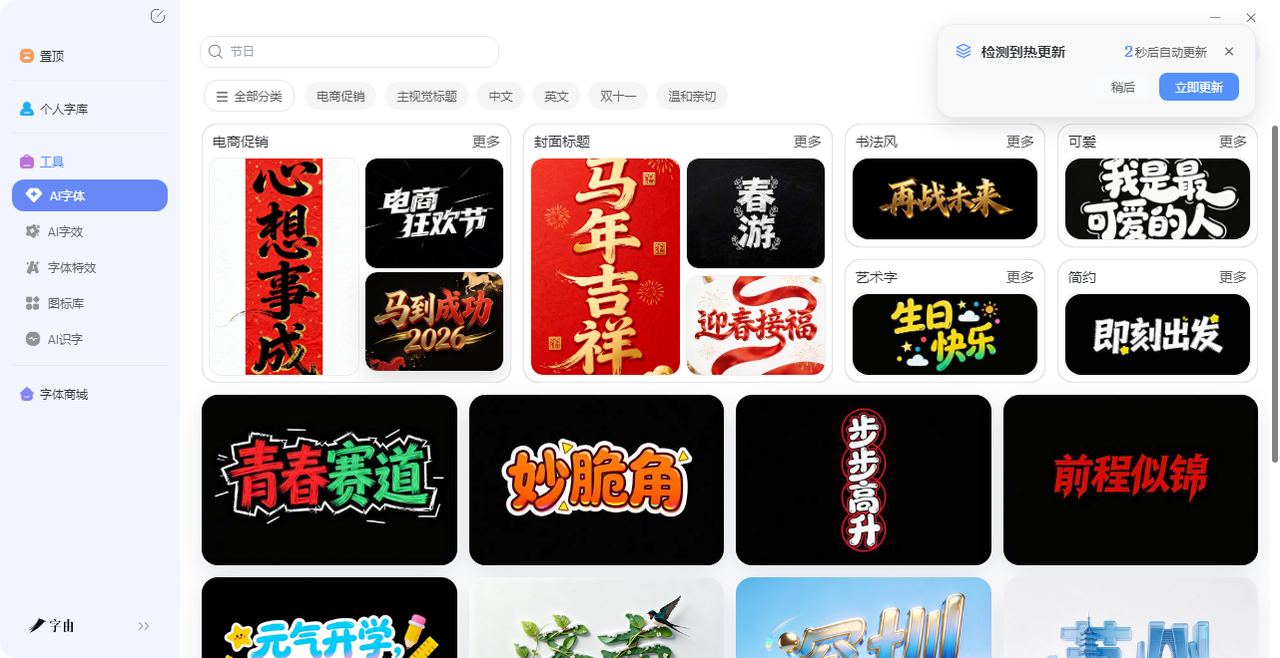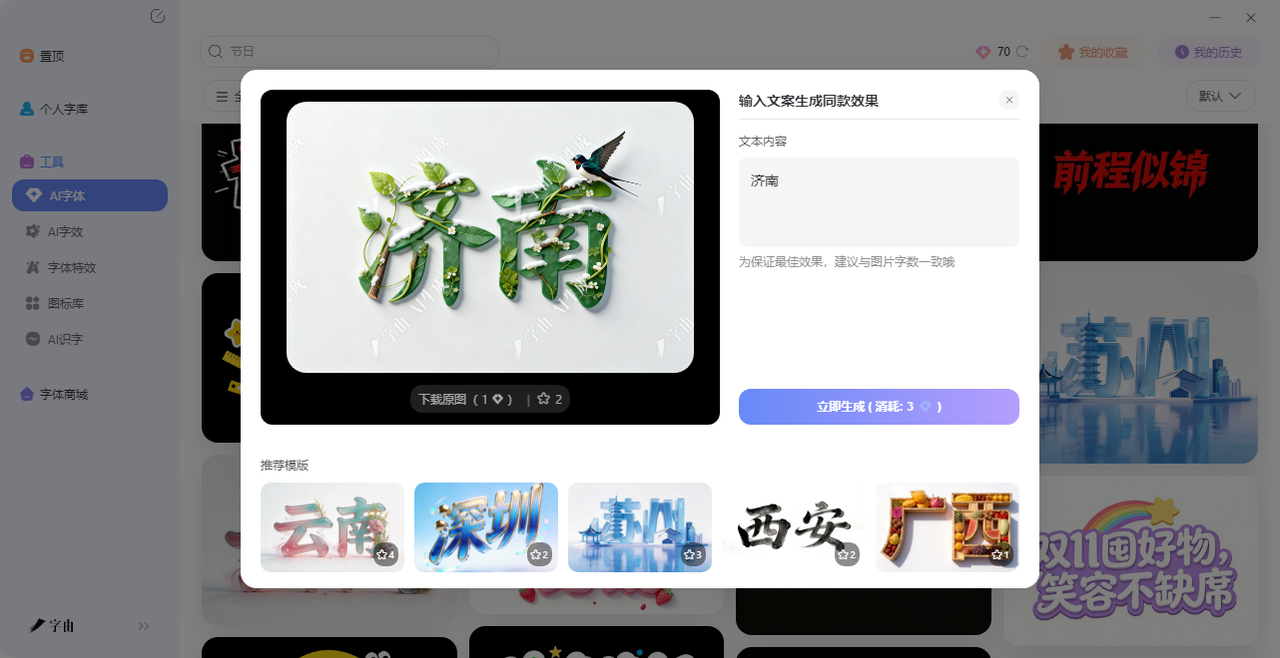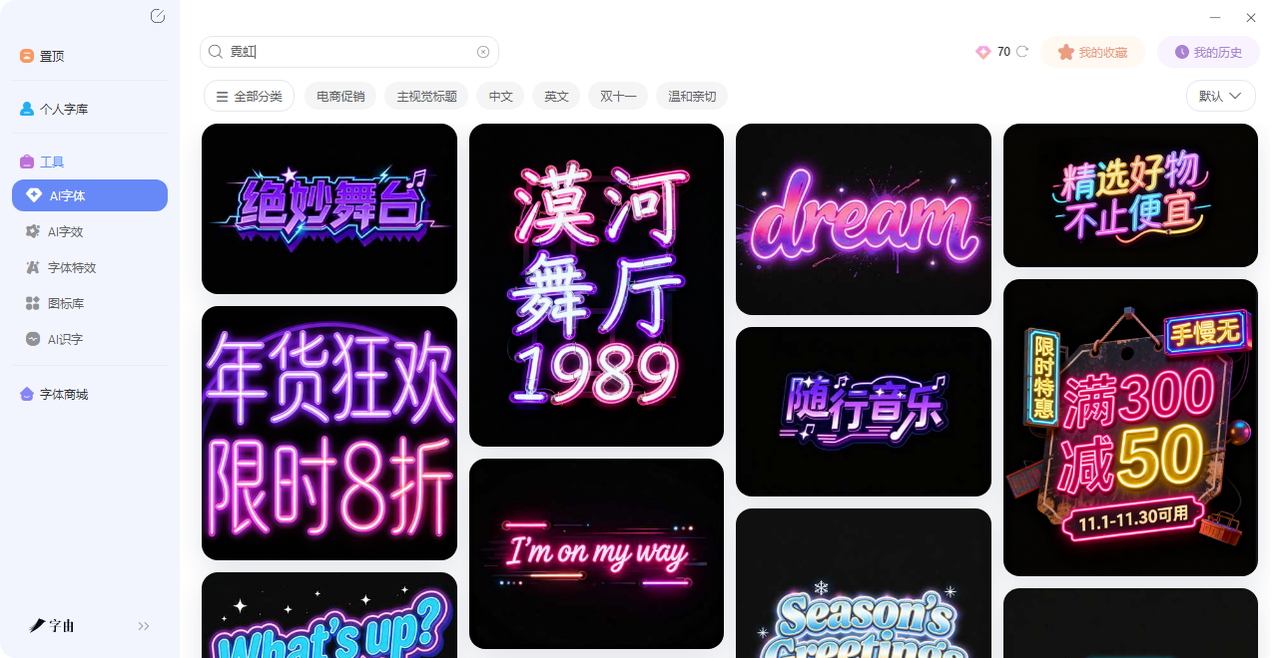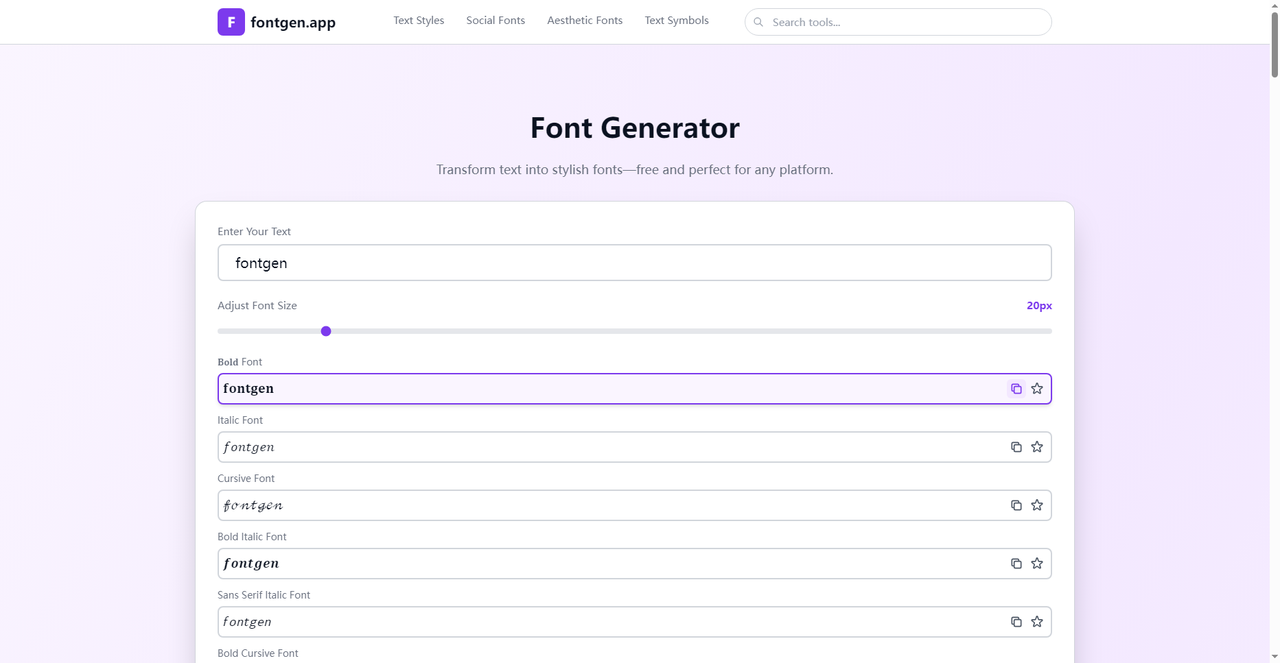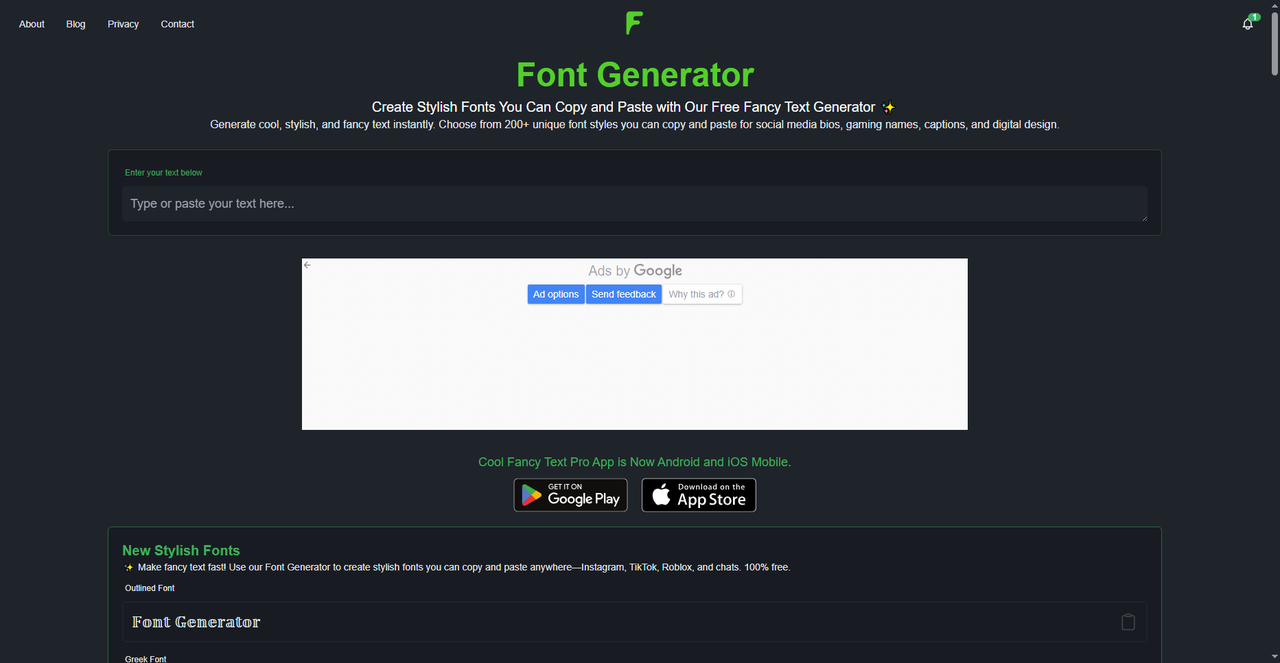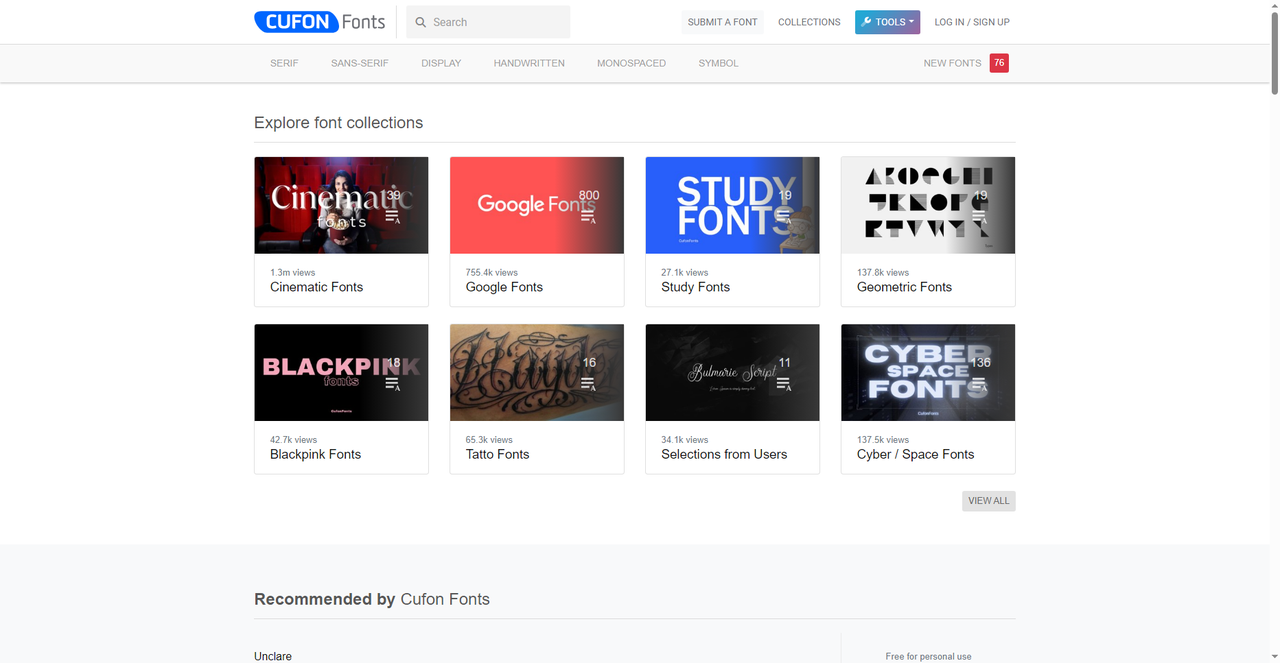
做设计的时候总觉自己的字体库里面的字体都太单调了,黑体、宋体、楷体,翻来翻去就这几个选项。想打出花体字、气泡字、带下划线的字,根本找不到入口。等到做设计的时间久了我才发现,根本不用装任何软件,网上有很多在线字体转换工具,输入文字,点一下,秒变几十种花式字体,复制粘贴就能用。在今天这篇文章里我就会介绍我私藏的4 个在线字体转换工具,需要的直接收藏。
字由的“AI字体”功能,能当在线字体转换器用。你不需要下载任何字体,打开网页就能把普通文字转成带特效的艺术字图片。和其他转换器不同,它生成的不是Unicode字符,而是高清艺术字图片,特别适合做海报、封面、视频标题。接下来我会教大家如何使用:
第二步:在搜索框里输入你想要的效果,比如“霓虹”“金属”“国潮”“手写”“3D”,系统会筛出对应的模板。每个模板都是一个现成的“转换效果”——你输入普通文字,它输出带特效的艺术字图片。
第三步:选一个模板,点击“做同款”,把模板里的文字换成你自己的,点“立即生成”,等20-30秒,就能拿到一张高清艺术字图片。
第四步:下载透明背景PNG,直接拖进PS、Canva、剪映里用。整个在线字体转换过程不需要安装任何软件,打开网页就能完成。如果你不确定哪个模板合适,可以多试几个。每天送的免费算力点够你试两三个。我一般会先挑三四个看着顺眼的,都生成一遍,然后放在一起对比。哪个看着最顺眼就用哪个。比如做国潮海报,我会同时生成“万物生长”“芳华国色”“君有云”三个模板,放在设计稿里看看哪个和整体风格最搭。多花几分钟对比,效果会好很多。
字由的AI字体模板库非常丰富,按场景分好了类。做一次在线字体转换,你可以在几十种风格里挑:
• 霓虹灯管:带玻璃管质感的霓虹字,适合音乐海报、酒吧招牌
• 金属质感:拉丝不锈钢、铬金属高光,适合科技产品、工业风
• 国潮书法:水墨晕染、毛笔飞白,适合国风海报、传统文化
• 水彩晕染:边缘模糊、颜料渗开,适合文艺封面、手账标题
每种效果都有几十个模板,总能找到你喜欢的,并且在固定次数范围内完全免费。如果你不想生成图片,只想要可复制的花式文字怎么办?也没关系,字由本身也有海量的免费商用字体库,考虑到使用场景不同,字由AI字体更适合做设计图。
2、fontgen.app
第二个在线字体转换工具fontgen.app,它的界面非常简洁:顶部有一个输入框,输入文字后,下面会实时生成多种字体样式的预览。比如你输入“fontgen”,它会自动生成:
• Bold Font(粗体)
• Italic Font(斜体)
• Cursive Font(手写体)
• Bold Italic Font(粗斜体)
• Sans Serif Italic Font(无衬线斜体)
• Bold Cursive Font(粗手写体)
每个样式下方都有“☆”图标,可以收藏喜欢的字体。还可以调整字体大小。点一下样式旁边的复制按钮,就能把转换后的文字复制到剪贴板,直接去微信、微博、Instagram粘贴。这个在线字体转换工具完全免费,不用注册,适合快速生成社交媒体文案。我经常用这个工具做朋友圈文案。输入一句话,几秒钟就出来好几种风格。比如“周末愉快”可以转成手写体,发出去比系统字体有温度多了。而且它支持实时调整字号,复制之前可以预览效果。收藏功能也很实用,常用的几个样式点一下星标,下次直接点收藏夹就行。
3、Font Generator
第三个在线字体转换工具是一个功能更强大的Font Generator。它提供了150多种花式字体样式,输入文字后,下面会列出所有样式的预览,每个样式旁边都有“Copy”按钮。它还支持搜索功能,你可以直接搜“Cursive”“Bubble”“Gothic”等关键词,快速定位想要的风格。页面底部还提示有手机App,可以在Google Play和App Store下载,随时随地做在线字体转换。这个工具的样式分类很细,包括:
• Outlined Font(描边字体)
• Bold(粗体)
• Italic(斜体)
• Cursive(手写体)
• Bubble(气泡字)
• Gothic(哥特体)
而且完全免费,不用注册,复制粘贴就能用。它的搜索功能特别好用。有时候想要一种“故障风”的字体,直接搜“Glitch”就能出来。不像有些工具要一页页翻。而且它支持关键词联想,输入“bub”就会自动推荐“Bubble”。我上次做游戏昵称,搜“Gothic”出来好几款哥特体,选了一个最顺眼的,复制到游戏里,十分出效果。
4、Cufon Fonts
最后一个在线字体转换工具其实是Cufon Fonts 网站的字体合集页面。虽然它主要是一个字体下载站,但它的“专题合集”功能可以帮你快速找到特定风格的字体,然后下载使用。这不算是直接的“转换”,但如果你想要某种特定风格的字体,比如“Cinematic Fonts”(电影感字体)、“Blackpink Fonts”、“Tatto Fonts”、“Cyber/Space Fonts”,在这里可以直接找到下载链接。
下载后安装到电脑,就可以在任何软件里使用。这也是一种“转换”——把普通文字变成特定风格的字体。每个合集都有几十到上百款字体,点进去就能浏览。比如“Cinematique Fonts ”有1.3m views,说明很受欢迎。推荐字体有“Unclare”“Basmala”“Zara Amorett Free”“Hasibuan Font”等,下载前记得查看授权说明。我偶尔会来这里翻翻“Cyber/Space Fonts”合集,做科技感海报的时候用。里面的字体很多带有未来感,有的像电路板,有的像星空。虽然要下载安装,但胜在风格独特。而且每个合集都标注了浏览量,浏览量高的基本不会踩坑。